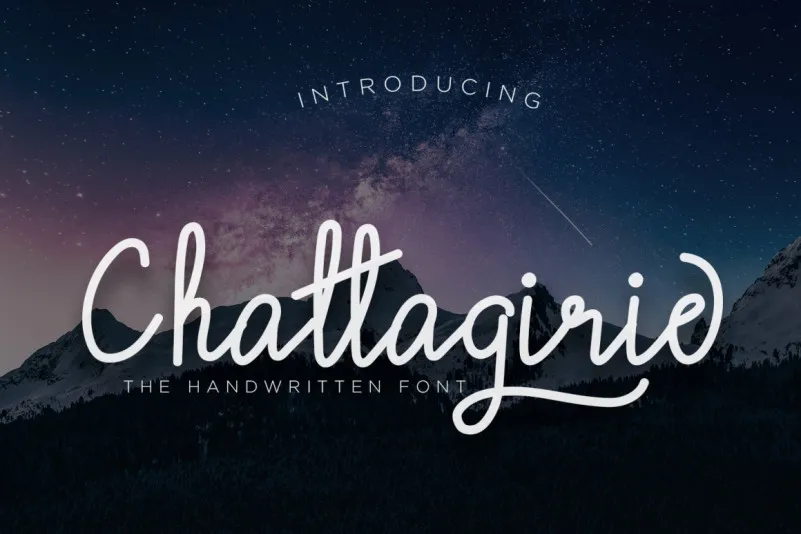
Chattagirie – Handwritten Font – Download Grátis
A fonte “Chattagirie – Handwritten Font” é perfeita para adicionar um toque único e encantador a uma variedade de projetos. Seja um projeto de branding, arte de mesa ou embalagem de produto, esse estilo elegante de escrita manuscrita complementará seu design de maneira única. Suave e versátil, a fonte “Chattagirie” será perfeita para criar identidades visuais memoráveis, desde rótulos até capas de livros, e pode ser usada com sucesso em mugs, cartões de convite ou até mesmo fotografias. Para quem quer expressar suas ideias de forma elegante, essa fonte é uma ótima opção para criar cartazes alegres, adesivos para presentes, selos para embalagens personalizadas e até mesmo design de logotipo. Sem dúvida, a “Chattagirie” oferece uma versão perfeita para criar um toque único em qualquer projeto que você esteja criando. Nas mãos certas, essa fonte transformará seus projetos de papel em obras de arte autênticas e únicas. Seja para presentear amigos ou familiares com cartões personalizados, ou para finalmente colocar a marca final no seu produto, a “Chattagirie” é sua melhor escolha. Essa fonte manuscrita certamente irá impressionar seus convidados e clientes com um toque único e autêntico.
Designer: Naharstd